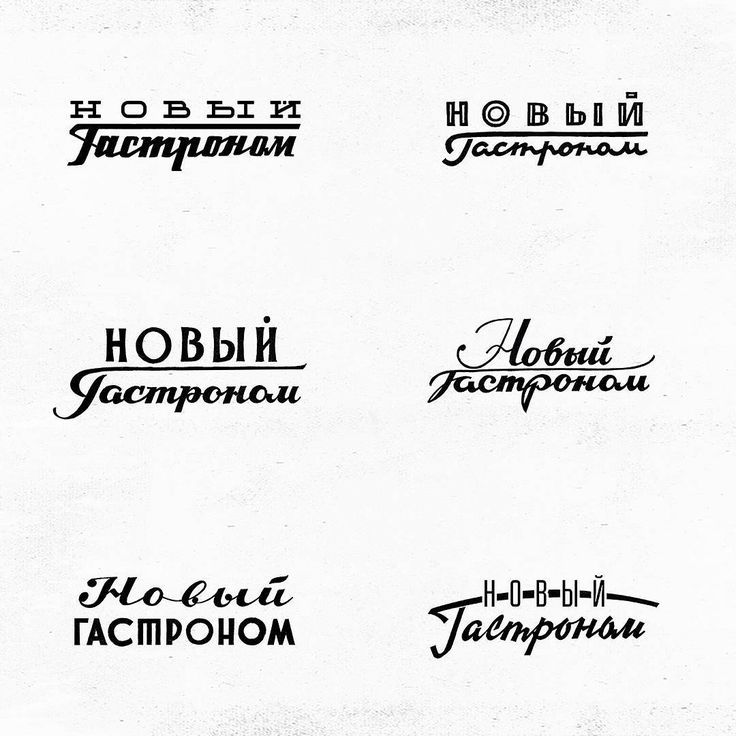
Многим кажется, что основой создания вывески является разработка ее дизайна. Отчасти это так, но самое ПЕРВОЕ, с чего начинается создание дизайна для вывески — это выбор шрифта. Ведь именно в текстовом посыле и заключается вся суть рекламных конструкций. Текст — это ПЕРВОЕ, на что обращают внимание люди, которые оказываются рядом с Вашей вывеской! О том, Как и Какой шрифт выбрать для наружной и внутренней вывески мы подробно расскажем в этой статье.
Рекламные вывески – это современный метод продвижения бизнеса, который требует основательного подхода. Если на биллборде или брандмауэре вместе с текстом стоит сопутствующее изображение, то для лайтбоксов и вывесок с объемными буквами основополагающей информацией является текстовый посыл. Необходимую информацию нужно уместить в 1-3 словах. Еще и так, чтобы она была легко читаемой и привлекательной.
После определения с содержанием и наполнением рекламы, для разработчика открывается вопрос выбора шрифта. Он должен быть гармоничным, читаемым и в меру броским.
Представляем Вам 16 самых популярных шрифтов, которые чаще всего используются маркетологами в наружной рекламе.
Каким должен быть размер шрифта для рекламной вывески?Удаленность точки продаж от потока пешеходов и людей в автомобильном транспорте является основополагающим фактором в выборе размера текста. Если расстояние сужается до 15-20 метров, то высота букв должна быть от 30 сантиметров. Если удаленность рекламной вывески более 50 метров, то оптимальной высотой считается показатель не менее 50 см.
При размещении вывесок или лайтбоксов на фасадах зданий важно выбрать оптимальную высоту букв. На строениях культурного наследия обычно допускаются вывески с высотой текста не более 25 см, на жилых или высотных строениях от 35 до 55 см.
Рекламные вывески, которые размещаются на уровне входа, над оконными проемами между 1 и 2 этажом, здесь важно соблюдать симметричность. При размещении светового короба или таблички: нужно чтобы удаленность от оконных рам или простенок была одинаковой.
Начертание шрифта для рекламной вывескиТак как наружная реклама воспринимается человеком всего на протяжении 5-7 секунд, то читаемость шрифта имеет большое значение.
Чтобы текст вывески сразу «бросался» в глаза и был запоминающимся, необходимо учитывать несколько рекомендаций по выбору типа шрифта:- — Рукописные, излишне курсивные шрифты в большинстве случаев не будут легко читаемыми и понятными. Их можно применять для давно состоявшихся компаний, где вычурно изображенный текст или название компании давно узнаваемы среди потребителей.
- — Для крышной конструкции лучше применять жирный шрифт.
- — Важно соблюдать оптимальный межбуквенный интервал, который не будет визуально накладывать буквы воедино.
Для надписи или названия из нескольких слов нужно соблюдать одинаковый межбуквенный и межстрочный интервал. - — Шрифты с засечками выглядят более официальными и могут использоваться для рекламы или вывески государственных учреждений, городских мероприятий и пр.
- — При размещении вертикальной вывески, лучше изображать буквы друг за другом или поворачивать их основанием к фасаду здания.
- — Если Вы хотите, чтобы вывеска гармонировала с архитектурой здания, то лучше подбирать шрифты без засечек, соответствующие стилю строения. Для арок и колон подойдет легкий курсив.
Преимущество световых вывесок – это возможность выделения текста с помощью светодиодной подсветки, добавления светового контура или выполнение текста неоном.
Идеальная рекламная вывеска от Первой Рекламной КампанииГлавное правило рекламы – примерять все на себе.
Даже если вы определились с концепцией и подобрали шрифт − попробуйте взглянуть на рекламу бегло и проанализировать, какие эмоции она у вас вызвала в первые 5 секунд, и насколько читаемым был текст. Если в момент чтения, цветовое исполнение текста и фона вас не отвлекало от быстрого прочтения информации, тогда все сделано правильно. К слову, следующая наша статья из серии «Дизайн в наружной рекламе» будет посвящена именно цветовому сочетанию в наружной рекламе.
Как выбрать шрифт для наружной рекламной вывески, чтобы не ошибиться
Когда дизайнер выбирает из тысяч шрифтов те, что будет использовать в наружной рекламной вывеске магазина, он всегда старается убить как минимум трех зайцев.
Во-первых, шрифт должен привлекать внимание. Во-вторых, работать на пользу рекламы. В-третьих, ее украшать.
- Classic Comic sans
- Etna sans serif
- Proxima nova
- Futura PT
Какой шрифт лучше всего подходит для большого знака?
Какой шрифт лучше всего подходит для вывесок? Любое количество шрифтов без засечек подходит для больших вывесок, но самые популярные варианты относятся к вариантам Arial, Helvetica и Bebas благодаря их четкости и удобочитаемости крупным шрифтом и на расстоянии. Профессионалы рекомендуют печатать текст крупным, жирным и темным, располагая при этом его на более светлом фоне.